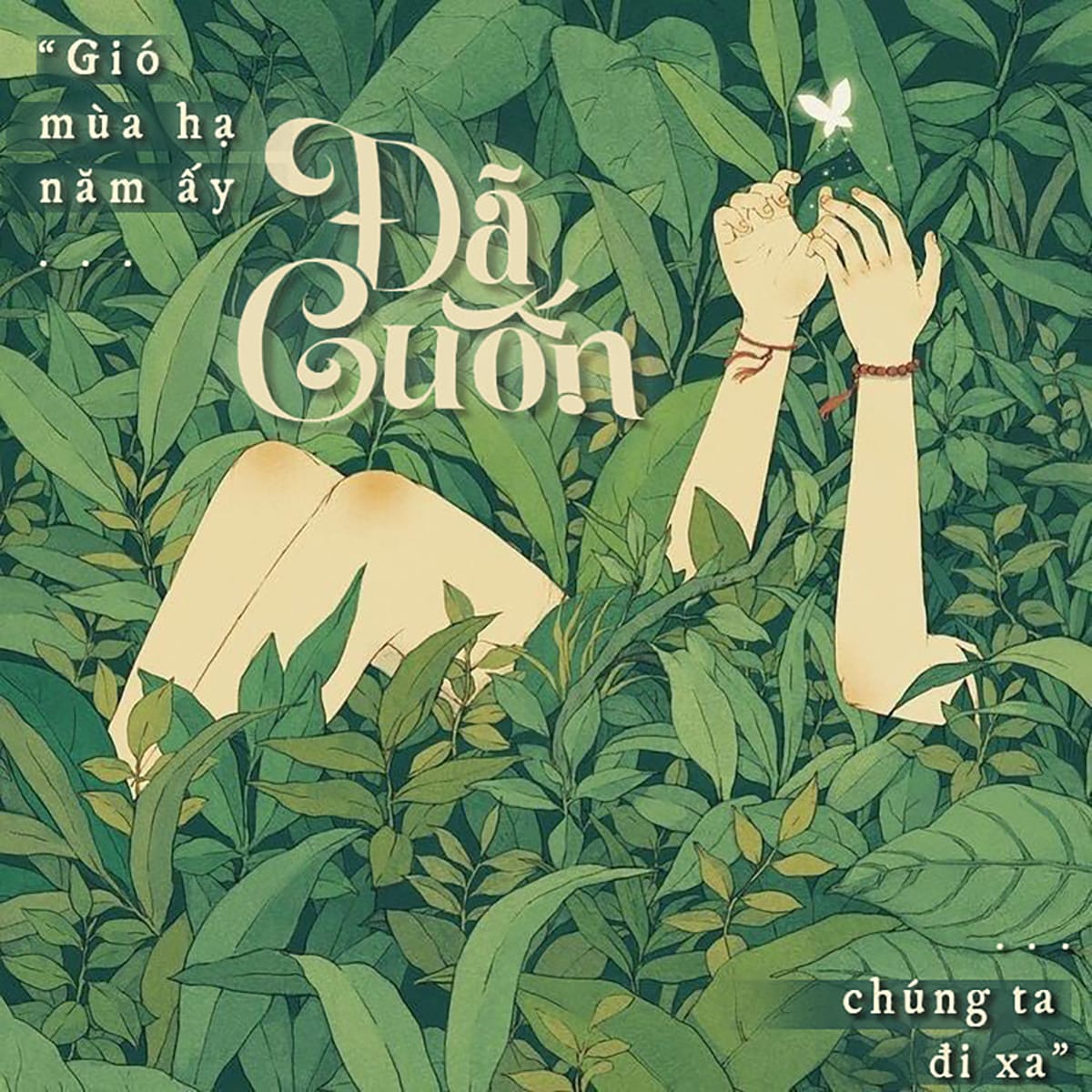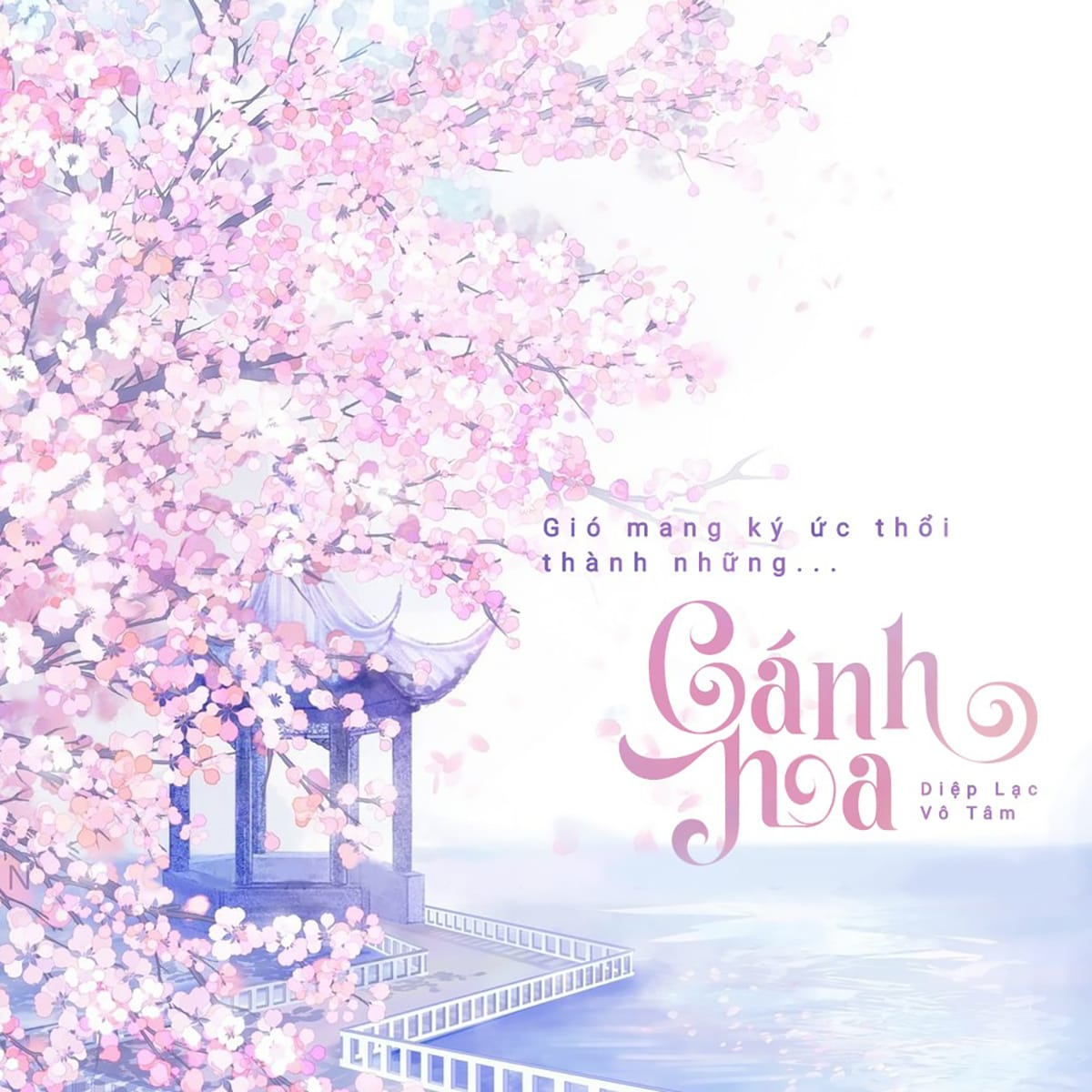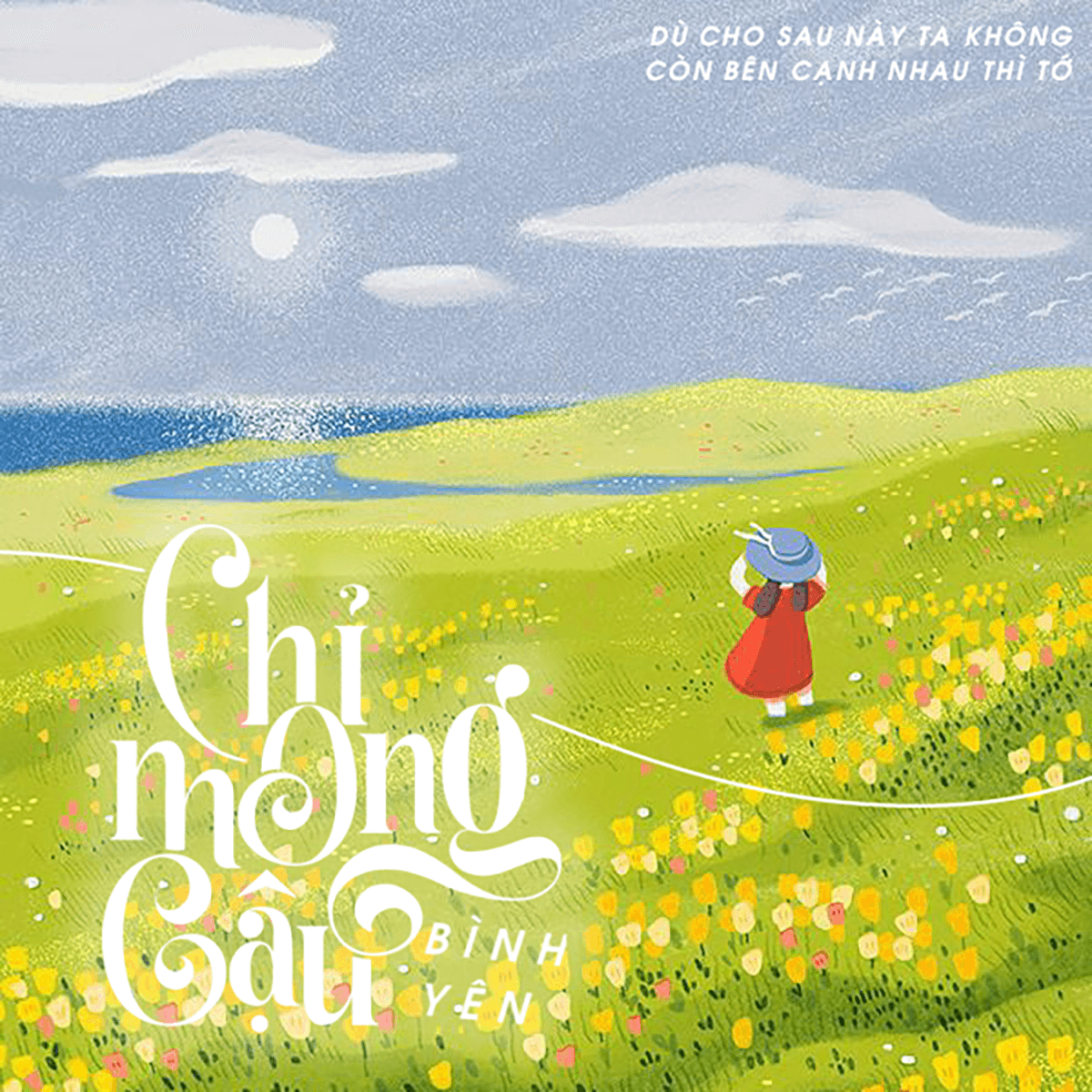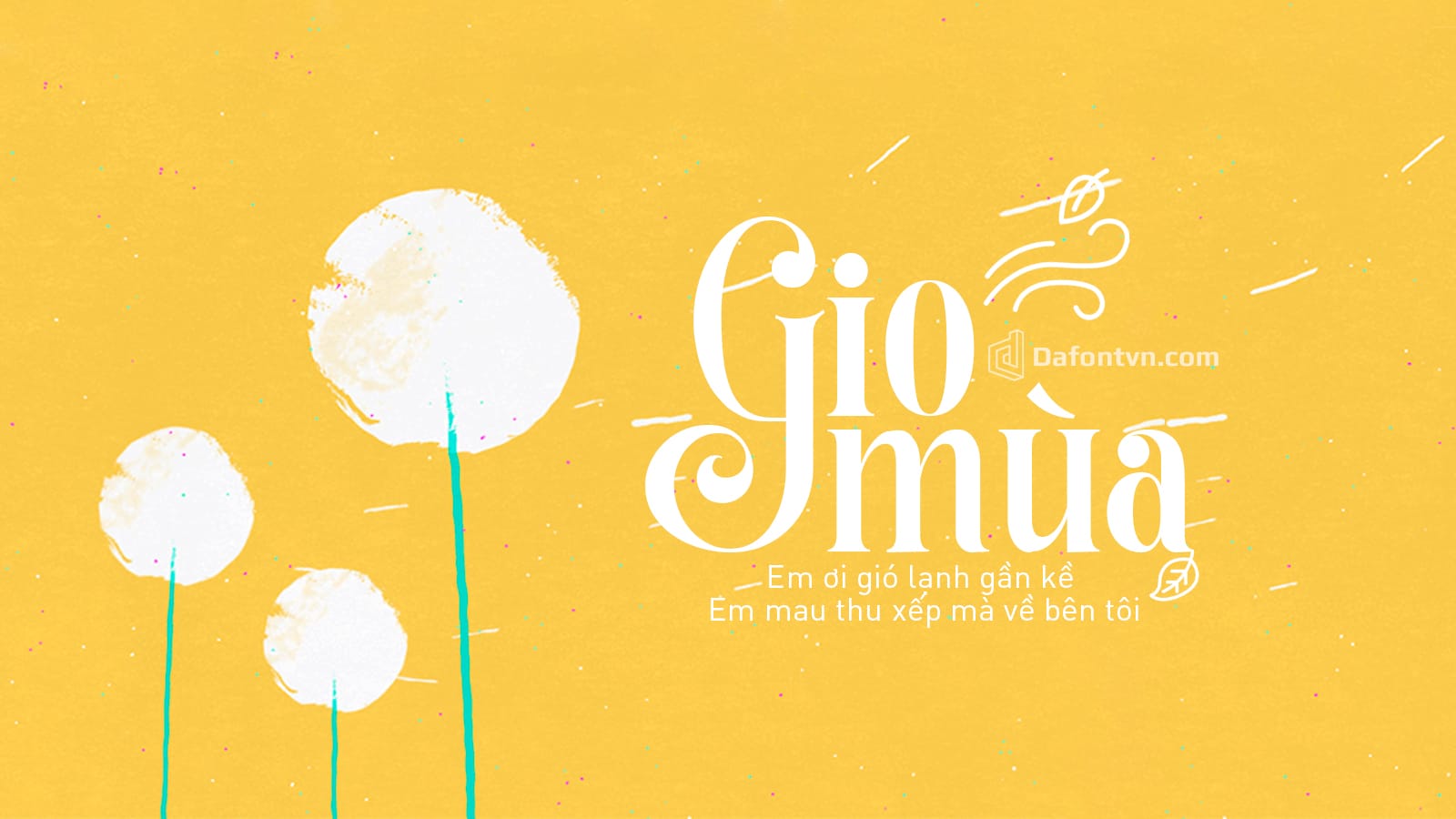
Font Melange Việt Hóa – là một font chữ serif lấy cảm hứng từ những thiết kế retro, nhưng font vẫn mang một dáng vẻ hiện đại mạnh mẽ. Phông chữ bao gồm các ký tứ viết hoa và viết thường thay thế đầy phong cách. Một font chữ khá phù hợp cho các thiết kế làm tiêu đề, thương hiệu, lời mời, tiêu đề, blog, typography và nhiều thiết kế khác nhau.Font được việt hóa đầy đủ, kerning, chỉnh sửa lại và tối ưu, việt hóa bởi NVN.